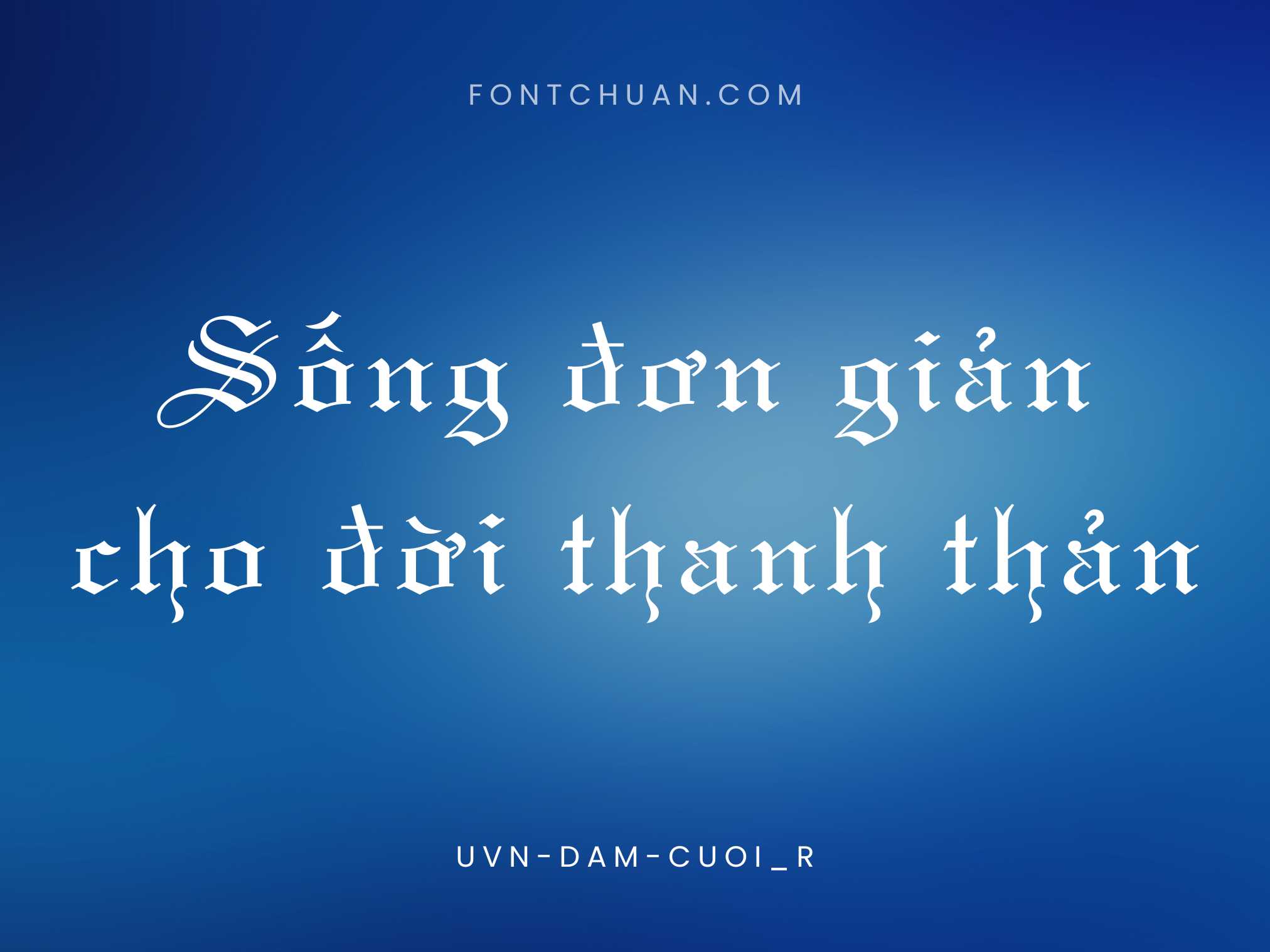
Font UVN Dam Cuoi Việt Hóa
UVN Đám Cưới là một phông chữ blackletter mang phong cách cổ điển với các chi tiết phức tạp, lấy cảm hứng từ nghệ thuật gothic. Phông chữ này có các nét chữ sắc nét, góc cạnh và trang trí tinh xảo, tạo nên vẻ ngoài lịch sử và trang trọng. UVN Đám Cưới hỗ trợ đầy đủ các ký tự tiếng Việt, giúp người dùng dễ dàng sử dụng trong các dự án sáng tạo liên quan đến văn hóa Việt Nam.
Với thiết kế độc đáo và nghệ thuật, UVN Đám Cưới phù hợp cho các ứng dụng như thiệp mời, tiêu đề sách, thiết kế logo và các ấn phẩm nghệ thuật. Trong lĩnh vực sự kiện, phông chữ này có thể được sử dụng trong các dịp như lễ hội, lễ cưới và các sự kiện văn hóa. Ngoài ra, UVN Đám Cưới còn là một Font chữ ảnh cưới lý tưởng, giúp trang trí các album cưới, thiệp cưới và các sản phẩm lưu niệm, mang đến sự sang trọng, tinh tế và ấn tượng cho các thiết kế. Font này cũng thích hợp cho các ngành nghề như thiết kế đồ họa, nghệ thuật trang trí và xuất bản.